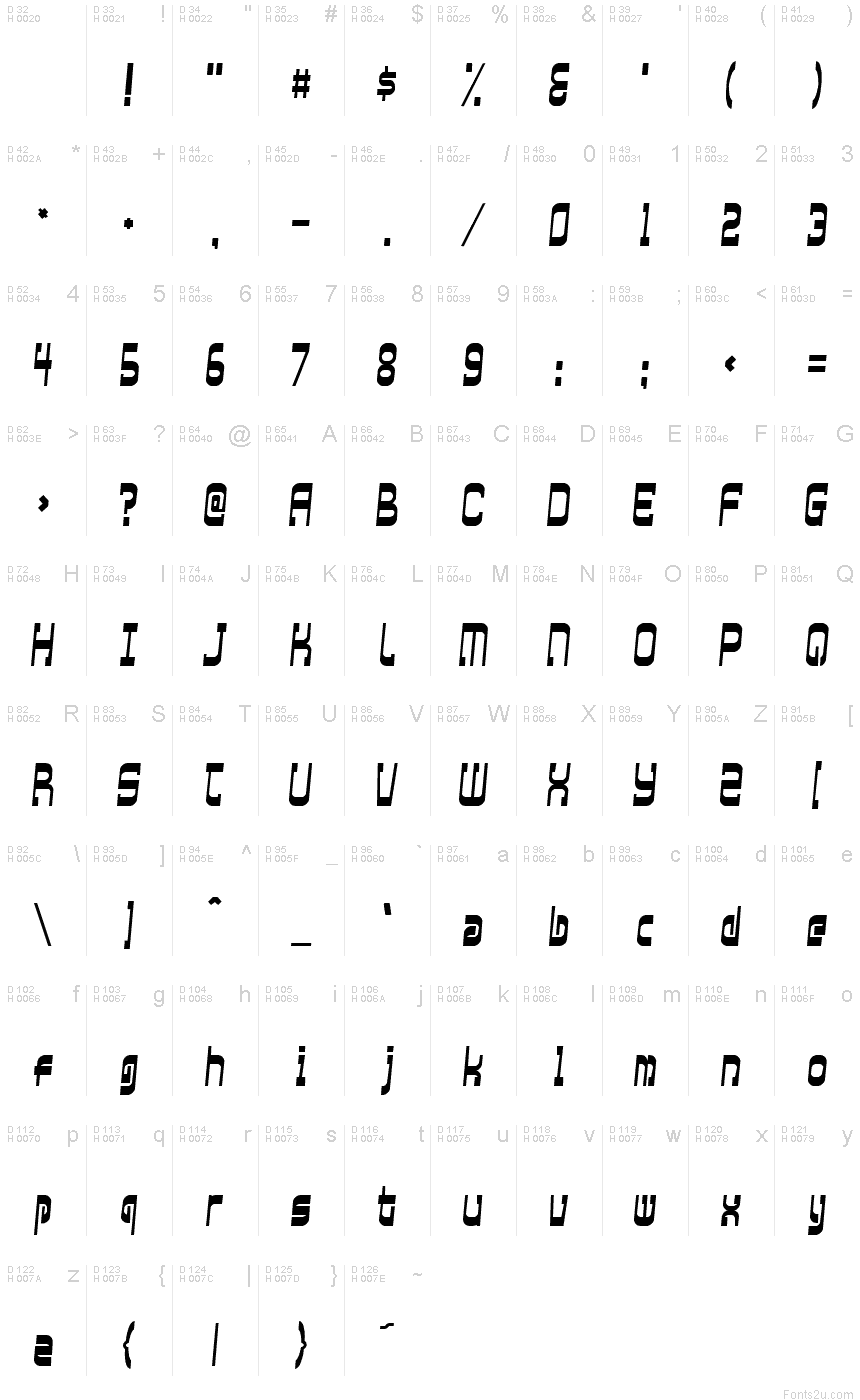
Xtraordinary od Jakuba Fischera je futuristické bezplatné titulkové písmo s nádechem sci-fi konce 70. let. Písmena kombinují široké zaoblené rohy s těsnými, téměř modulárními spoji, díky čemuž působí písmo proudnicově a lehce experimentálně, nikoliv však chladně geometricky.
Hodí se pro hudební obaly, retro-tech branding, titulky plakátů, herní grafiku a obálky časopisů, kde krátké slovo potřebuje ten správný hladký „strojový“ šmrnc. Jako bezplatné písmo také skvěle funguje pro titulní karty a logotypy, protože kompaktní křivky a vykrojené vnitřní prostory dodávají i jednoduchým nápisům výraznou, technicky propracovanou siluetu.
Xtraordinary